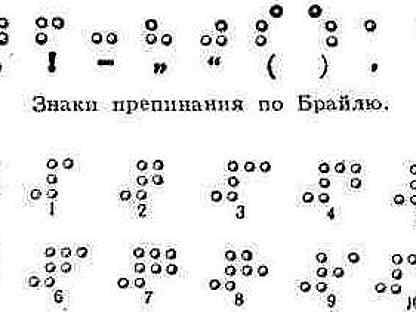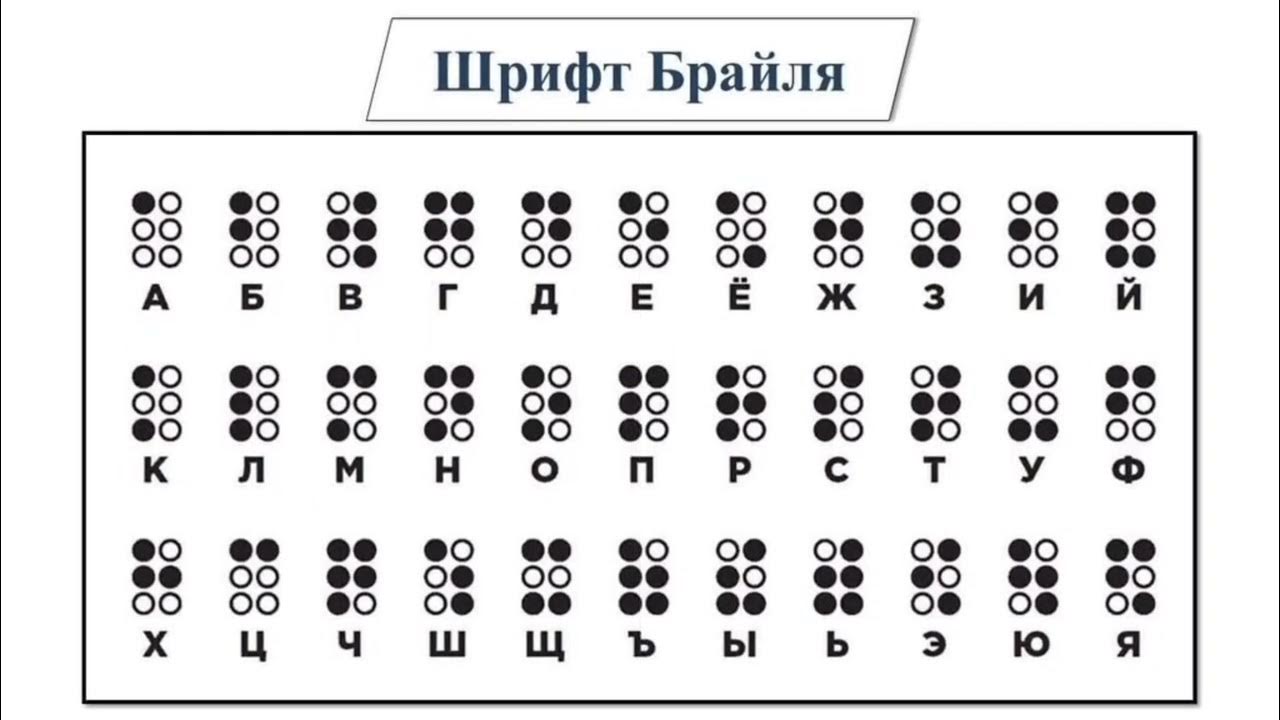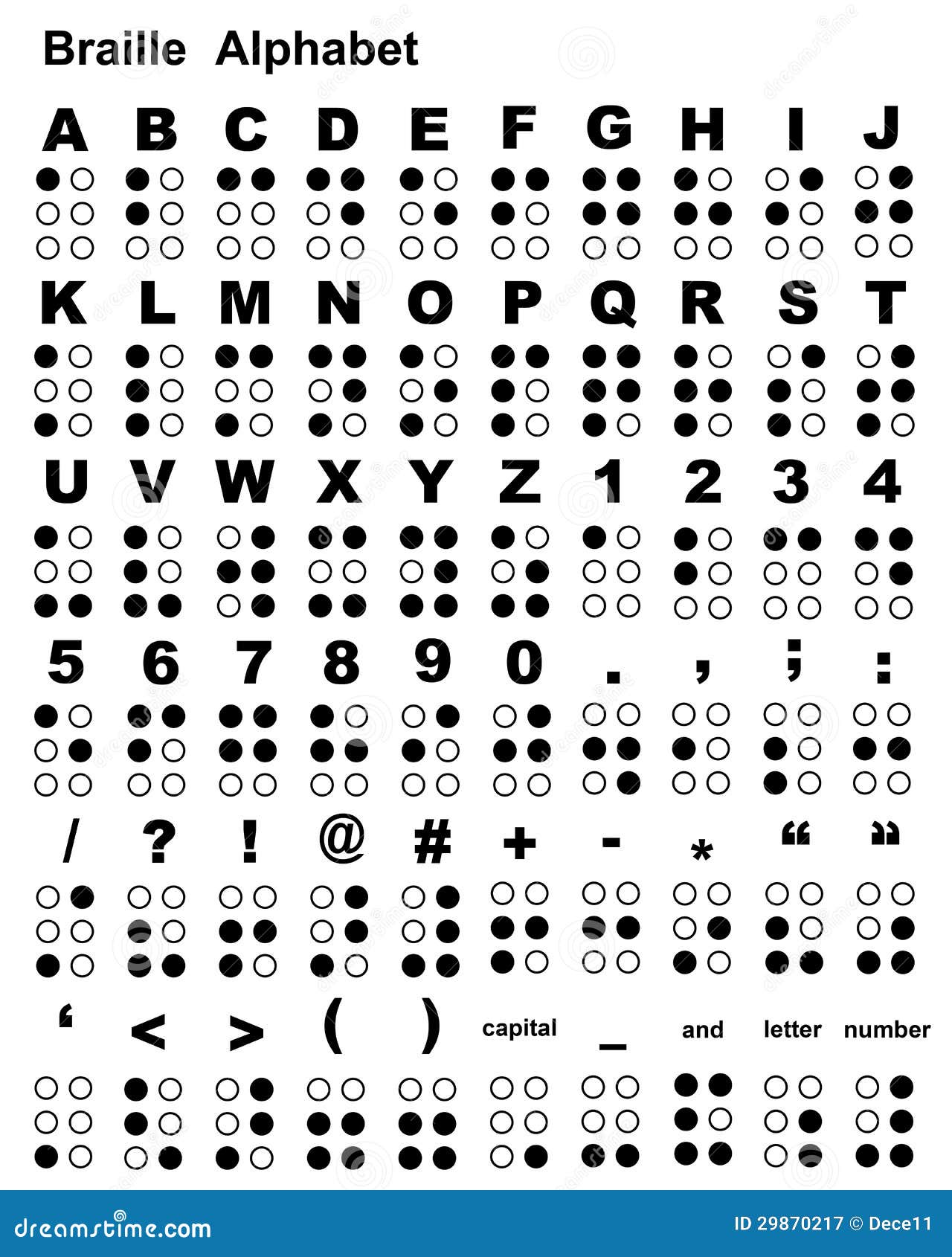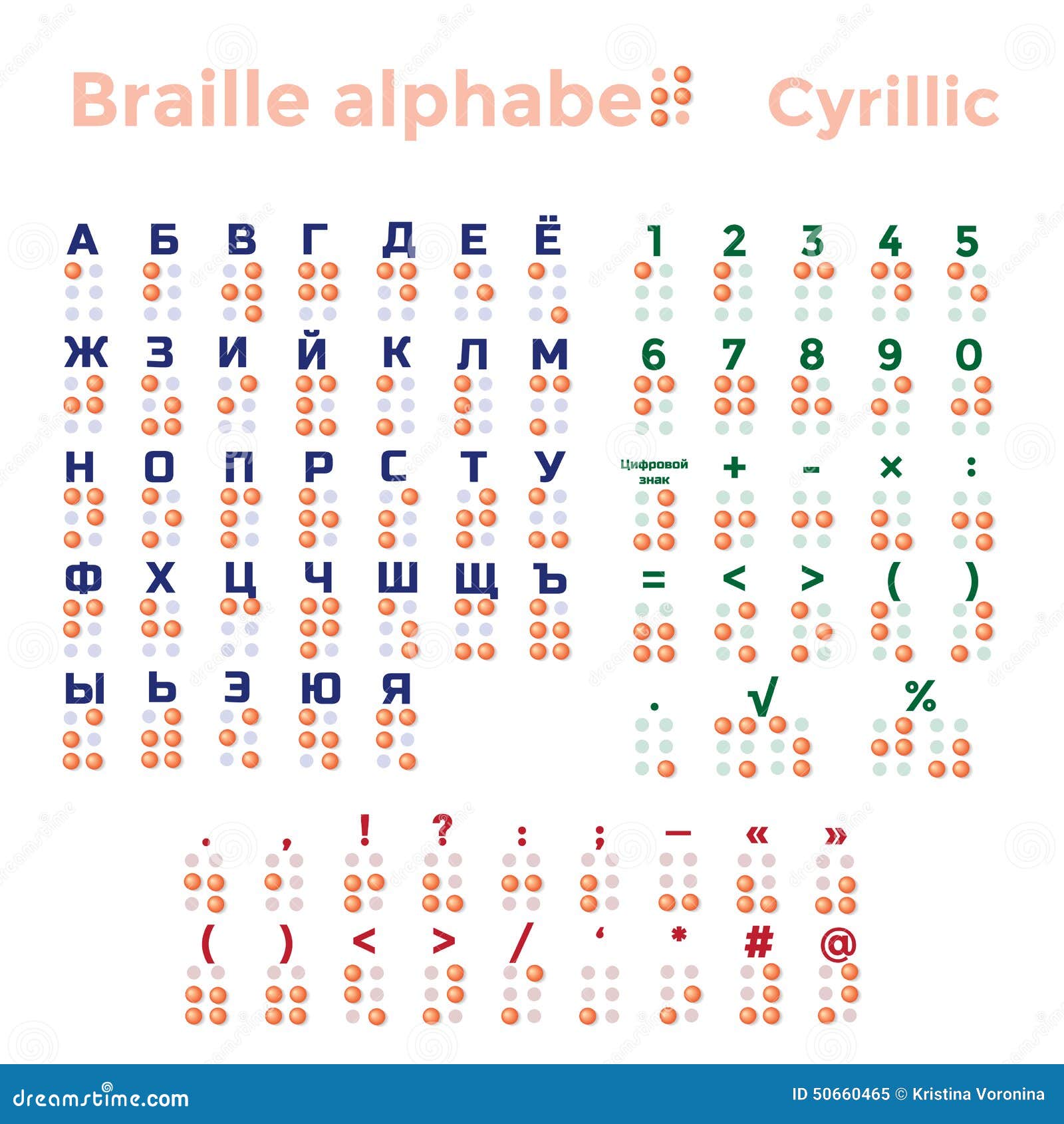
Как правильно использовать нумерацию точек в шрифте Брайля: советы и рекомендации
На данной странице вы найдете подробную информацию о системе нумерации точек шрифта Брайля, ее особенностях и применении. Мы предлагаем практические советы, которые помогут вам разобраться в структуре и правилах использования шрифта для создания доступных материалов для людей с нарушениями зрения.
Шрифт Брайля основывается на комбинации из 6 точек, расположенных в два столбца по 3 точки в каждом. Каждая точка имеет свое место в системе нумерации, что позволяет формировать буквы, цифры и знаки препинания.
Для понимания структуры шрифта важно знать, что каждая точка может быть поднята или не поднята. Это создает различные комбинации, которые представляют собой символы или буквы, легко воспринимаемые на ощупь.
Нумерация точек в шрифте Брайля начинается с верхней левой точки, которая считается точкой Далее идут точки 2, 3 и 4, которые продолжают формировать комбинации для алфавита и цифр.
При использовании шрифта Брайля важно помнить, что разные комбинации точек соответствуют разным символам, например, цифры и буквы могут использовать одну и ту же систему, но с различными модификациями.
Для правильного чтения и записи шрифта Брайля важно учитывать, что каждая точка может быть расположена в одном из 6 возможных мест, и все они должны быть правильно обозначены для обеспечения доступности информации.
Использование шрифта Брайля в образовательных и социальных сферах помогает людям с нарушениями зрения успешно ориентироваться в текстовой информации, обеспечивая доступ к знаниям и информации.
Шрифт Брайля можно использовать не только для букв и цифр, но и для обозначения математических символов, музыкальных знаков и других специальных знаков, что делает его универсальным инструментом.
Для удобства чтения текста на шрифте Брайля важно правильно форматировать материалы, например, использовать достаточно крупные символы и четкие интервалы между строками.
Современные технологии позволяют создавать устройства, которые могут считывать текст на шрифте Брайля и преобразовывать его в звуковую информацию, что значительно улучшает доступность информации для людей с нарушениями зрения.
Использование шрифта Брайля способствует интеграции людей с нарушениями зрения в общество, обеспечивая их право на равные возможности в обучении, работе и повседневной жизни.